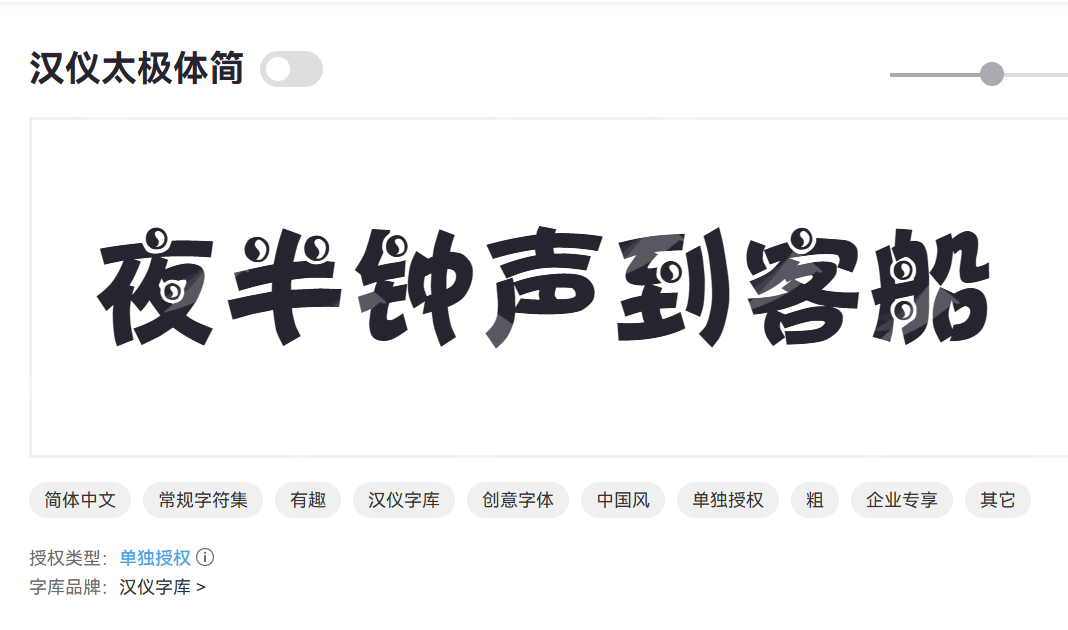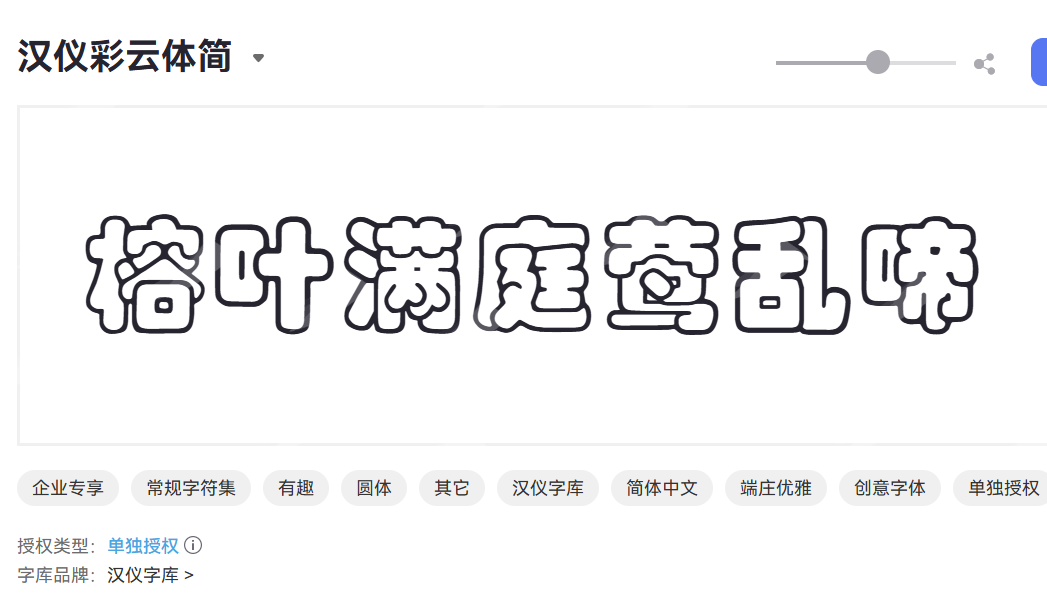
空心字体大全,收集了 8 款好看的空心字体
你是否曾被那些只有轮廓、内部“空空如也”的文字所吸引?它们轻盈、时尚、充满设计感,有时显得未来科技,有时又带着复古情怀。没错,我说的就是空心字体。本文给大家收集了 8 款好看的空心字体。
什么样的字体叫空心字体
空心字体我比较喜欢把它们当成一种艺术字体,让文字不再仅仅是信息载体,而成为一种具有独立美感的艺术形式。
空心字体就是指那些只有笔画的轮廓线,而内部空间是透明或填充有其他元素的字体。与我们日常所见的实心字体不同,一个充满力量感的粗实字体,如果变成空心,它会立刻变得轻盈起来。
空心字体的特点
空心字体在平面设计、品牌Logo、海报、包装、网页设计、甚至服装印花等领域都有着广泛的应用。因为它们具有下面这些特点。
- 轻盈的未来感
内部的“空”赋予了文字轻巧、透气的特质,非常适合需要营造现代感、时尚感、未来感的场景。
- 表达个性
空心字体本身就带有一种强烈的艺术气息。无论是简洁的几何线条,还是流畅的手写笔触,一旦变成空心,都能立刻提升文字的艺术格调,为品牌或作品注入独特的个性。
- 温暖的强调
通常在一些设计中,空心字体可以作为标题或特定信息的强调手段。
- 可玩性
设计师可以利用空心字体的特性,进行二次创作。比如在空心内部填充不同的纹理、渐变色、照片,甚至动态效果,这都为创意设计提供了无限可能。
8款常用的空心字体
华康娃娃空心体
华康娃娃空心体是一款充满童趣和活力的创意字体。它继承了华康娃娃体系列圆润可爱的风格,并在此基础上加入了独特的“空心”设计,使得字形更加轻盈、通透,富有立体感和趣味性。
华康娃娃空心体字形圆润饱满,笔画处理活泼,充满儿童般的纯真与烂漫。特别适合儿童产品包装、教育出版物、卡通动漫、节日海报、社交媒体图文、主题公园标识等,营造轻松活泼的氛围。
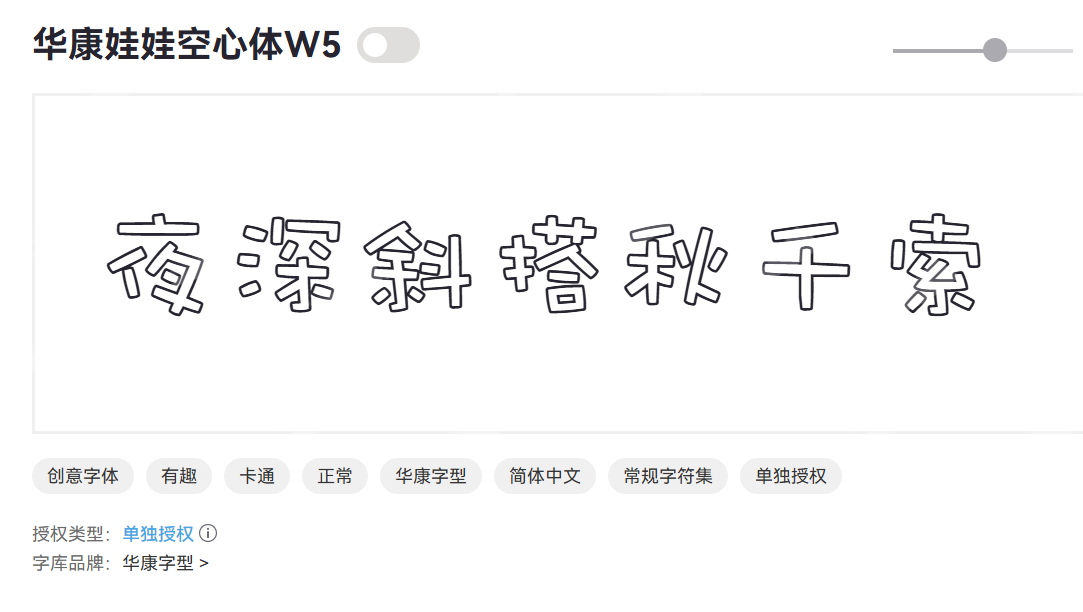
汉仪太极体
汉仪太极体是一款蕴含东方哲学的创意字体。它从中国传统文化中的“太极”理念中汲取灵感,将阴阳、刚柔、动静相生的意境融入到字形设计中,呈现出独特的韵律感和平衡美。
汉仪太极体适用于追求文化内涵、国风美学等场景,能有效提升品牌的高端感和艺术格调。
汉仪彩云体
汉仪彩云体是一款充满浪漫与梦幻色彩的艺术字体。它的设计灵感来源于天空中的彩云,笔画飘逸、柔美,犹如云朵般轻盈舒展,为文字赋予了诗意和浪漫的视觉感受。
汉仪彩云体笔画线条流畅,起伏有致,仿佛云彩般自然舒展。适合用于婚庆请柬、情人节促销、时尚杂志、化妆品广告、女性品牌设计等场景,能有效传达柔美、浪漫的情感。
汉仪双线体
汉仪双线体是一款极具现代感和科技感的几何字体。对于经常对接科技和游戏产品的我来说,我经常使用这款空心字体,独特的双线设计能瞬间抓住用户注意力,有效突出标题和重要信息。
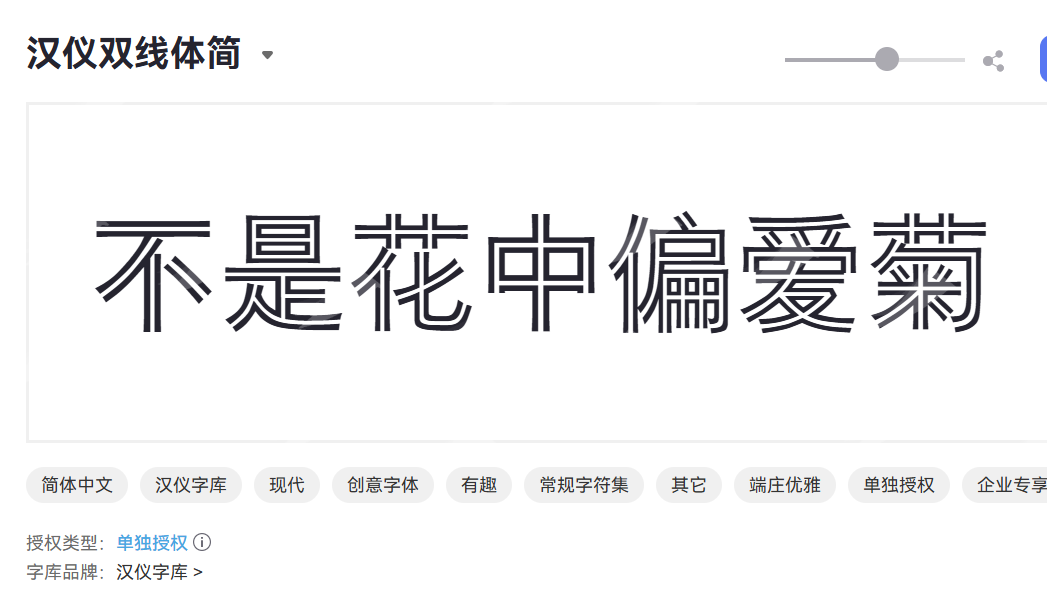
汉仪白棋体
汉仪白棋体是一款兼具沉稳与灵动的创意字体。笔画末端和转角处处理得圆润流畅,给人以温和、亲切的感觉。
这款空心字体适用于追求高品质、简约而不失品位的品牌,如高端餐饮、文化艺术机构、生活美学品牌等。
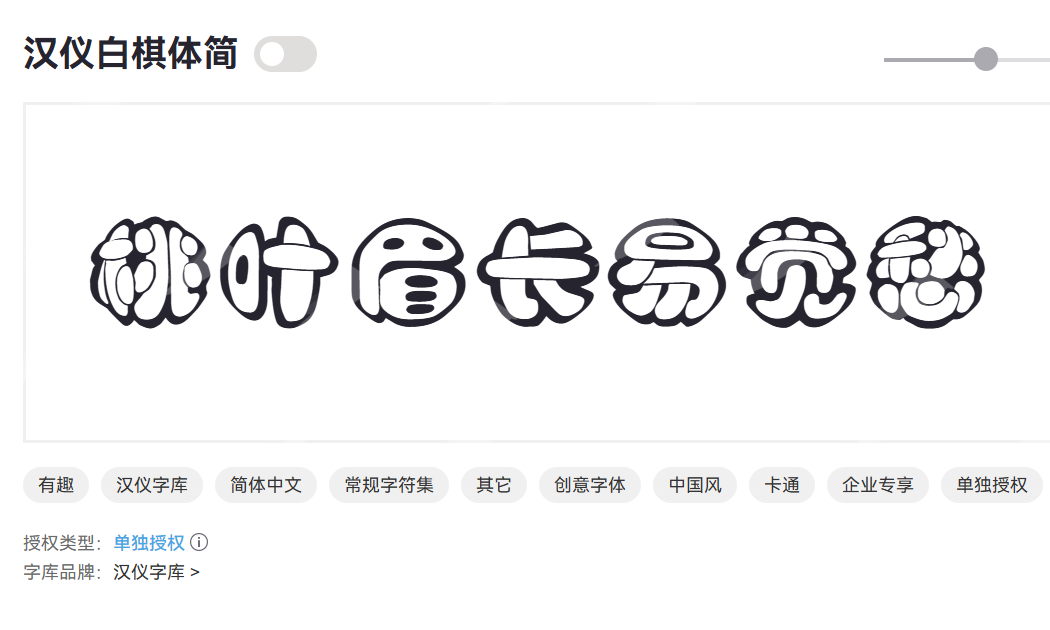
汉仪立黑
汉仪立黑是一款刚劲有力、结构端正的粗体黑体字。它在传统黑体的基础上,强化了笔画的挺拔感和力度感,使得字体更加醒目、坚实,传递稳定与力量。
非常适合用于标题、广告语、企业宣传、工业产品介绍、安全警示等需要强调信息、展现力量和权威感的场景。
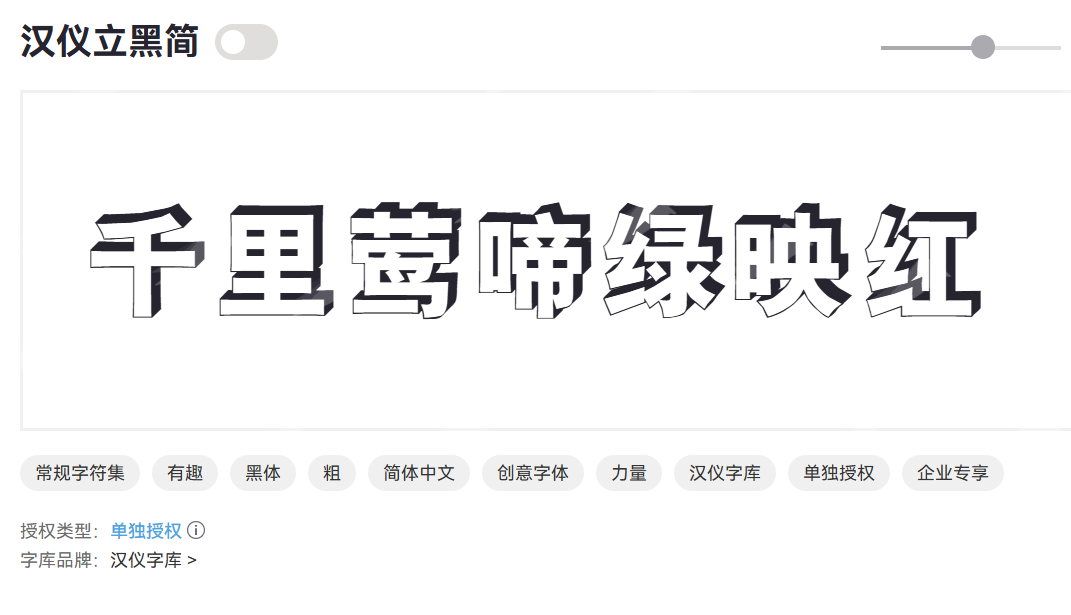
汉仪新蒂剪纸体
汉仪新蒂剪纸体是一款充满民族特色和艺术魅力的创意字体。它将中国传统的民间艺术——剪纸的独特风格融入到字体设计中,字形结构精巧,笔画之间仿佛有剪刀雕刻的痕迹,充满喜庆与文化韵味。
毫无疑问,我在做一些新年的设计作品时,经常使用这款空心字体。
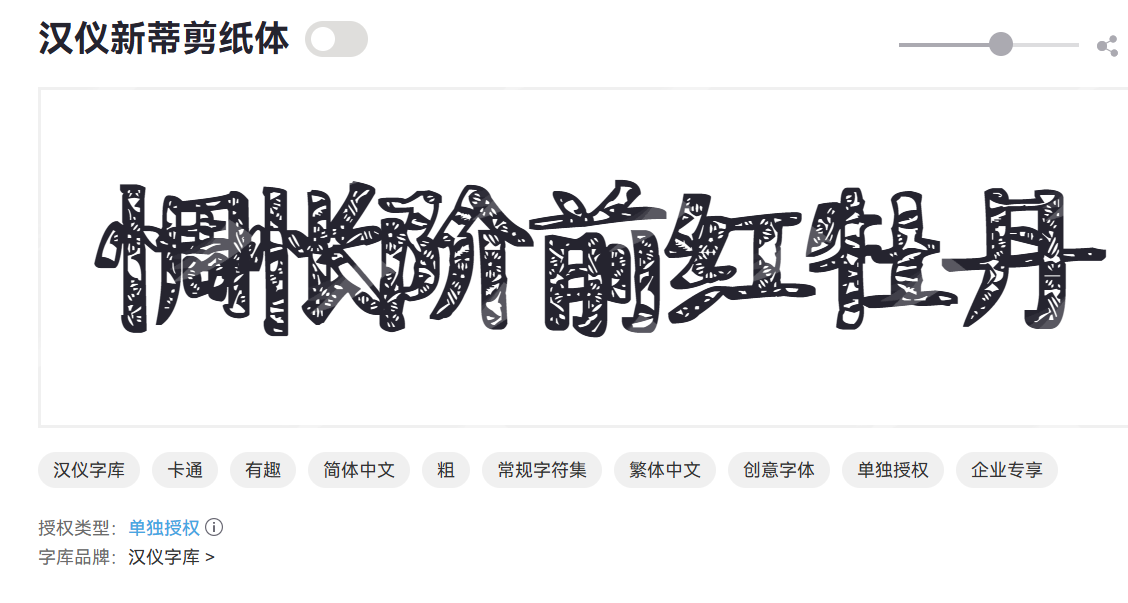
汉仪咪咪体
汉仪咪咪体是一款活泼可爱、充满亲和力的手写风格字体。笔画弯曲柔和,字形活泼,给人一种可爱的亲近感。
因为可爱的元素,汉仪咪咪体非常适合儿童读物、漫画、零食包装、休闲品牌等场景。